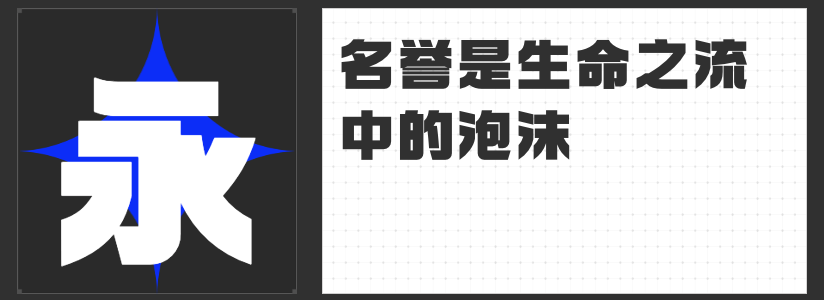
四款经典黑体推荐:以力量与美感重塑海报视觉张力
黑体,作为现代设计中最具代表性的无衬线字体,以其横平竖直的骨骼、清晰利落的轮廓,始终占据着海报设计的核心地位。它既是信息传递的“高效载体”,也是风格塑造的“视觉锚点”——从庄严的公告到先锋的艺术展,黑体总能用克制的笔触传递震撼的力量。本文精选四款风格各异的黑体字体,助你在海报创作中突破常规,打造兼具辨识度与艺术性的视觉语言。
一、励字综艺简繁
这款黑体以饱满的笔划填充空间为显著特征,在保持方正结构的同时,通过圆润的拐角处理消解了传统黑体的机械感。其笔划粗细均匀却暗藏张力,既保留了黑体的严谨秩序,又因适度的弧度增添了灵动气息。无论是作为主标题的视觉核心,还是辅助信息的层级支撑,都能以独特的“活泼严谨感”平衡画面,适合需要突破刻板印象的创意海报设计。
二、高手兵克柔黑体
传统黑体的棱角在此被巧妙化解——转折处的弧形过渡、撇捺的流畅收笔,让字体在保持力量感的同时,多了一分柔和的呼吸感。较粗的字重使其在远距离依然醒目,而微妙的曲线处理则避免了沉重感,适用于需要传递亲和力或人文气息的海报主题,如文化展览、公益宣传等场景。
三、励字超粗黑简繁
突破常规黑体的静态框架,这款字体通过笔划斜度设计与均衡的黑白分布,在方正中注入动势。超粗的笔划如雕塑般立体,方头方尾的结构强化了视觉冲击力,而斜向笔画的隐性引导线则让目光自然流动。无论是科技产品的硬核发布,还是运动品牌的激情宣言,它都能以“未动先声”的气势抓住观众视线。
四、励字励黑简
以超粗笔划与绝对方正构建视觉权威,这款字体剥离了一切装饰性元素,仅用纯粹的几何形态传递信息。无衬线、无粗细变化、无多余弧度的设计,使其成为需要绝对清晰度与仪式感的海报首选——从书籍封面到品牌标语,从活动主视觉到重点数据强调,它总能用最简洁的方式占据画面主导权。
黑体的魅力,在于它既能承载严肃命题,亦可玩转创意表达。这四款字体以不同的方式拓展了黑体的边界,为海报设计提供了更丰富的可能性。